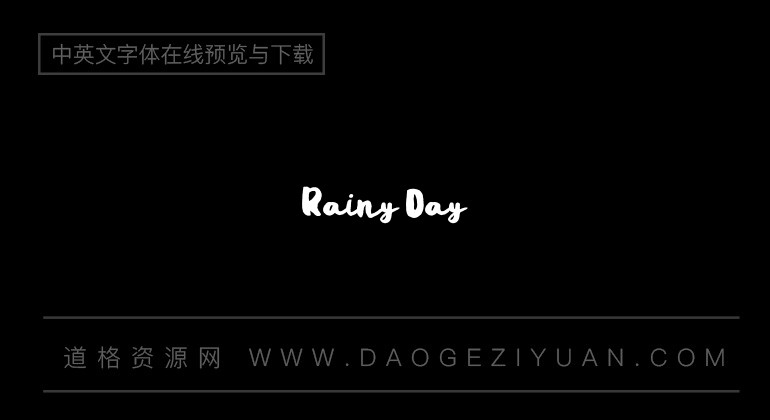
Rainy Day
Rainy Day 字体是一种手写笔迹字体,具有轻松、自然的感觉。它的字母形状看起来像是用水墨或彩笔书写的,笔画有一些模糊和涂抹的效果,让字体看起来更加真实和有趣。 这种字体适用于多种场景,比如卡片、海报、标语、广告、个人网站和博客等。Rainy Day 字体可以营造出一种轻松、温馨的氛围,让人们感到快乐和放松。
Rainy Day是一款非常不错的手写艺术字体,具有很好的视觉感,适合于文化类的宣传设计、商业类品牌的广告和产品包装设计以及个性化文字排版等较多场景。